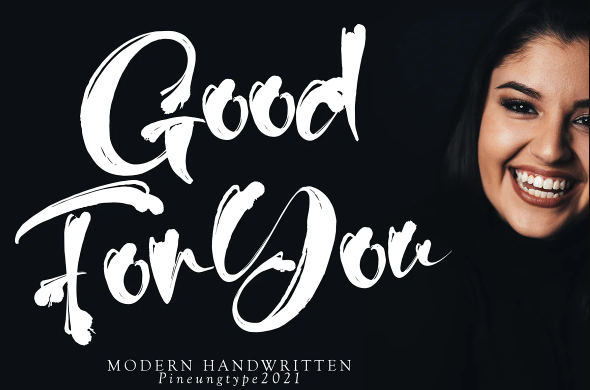
[Creativemarket] GoodForYou Font (2021)
Шрифт GoodForYou с новым стилем, этот шрифт идеально подойдет для различных проектов, например: цитаты, логотип, заголовок блога, плакат, обвязка, письмо, приглашение, канцелярские принадлежности и т.д....